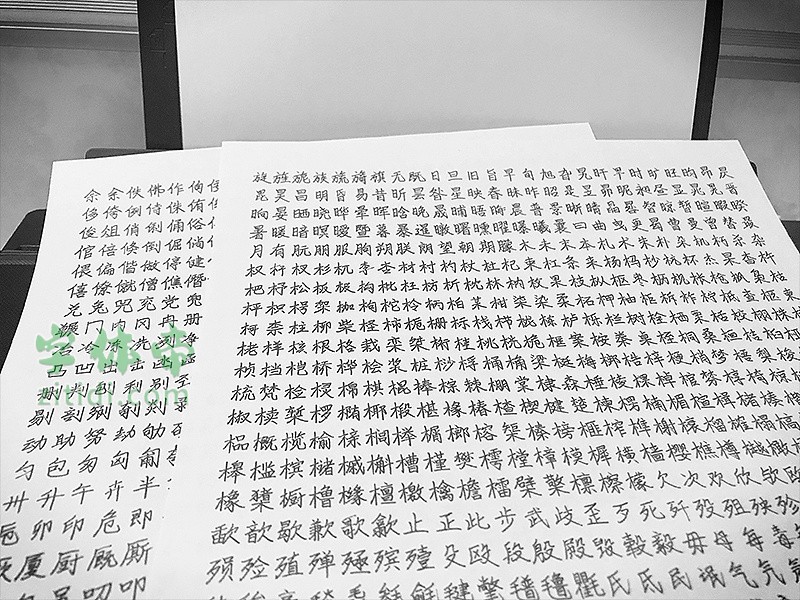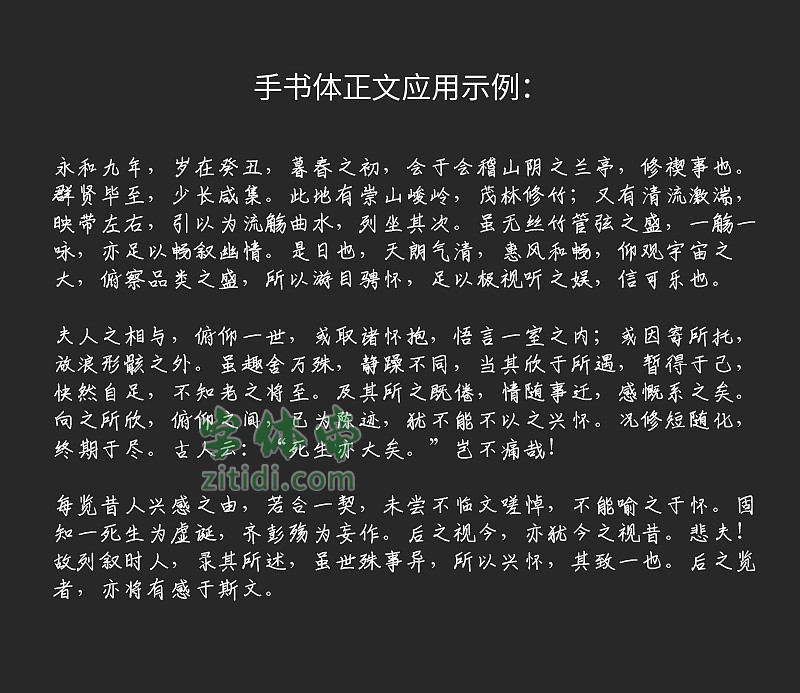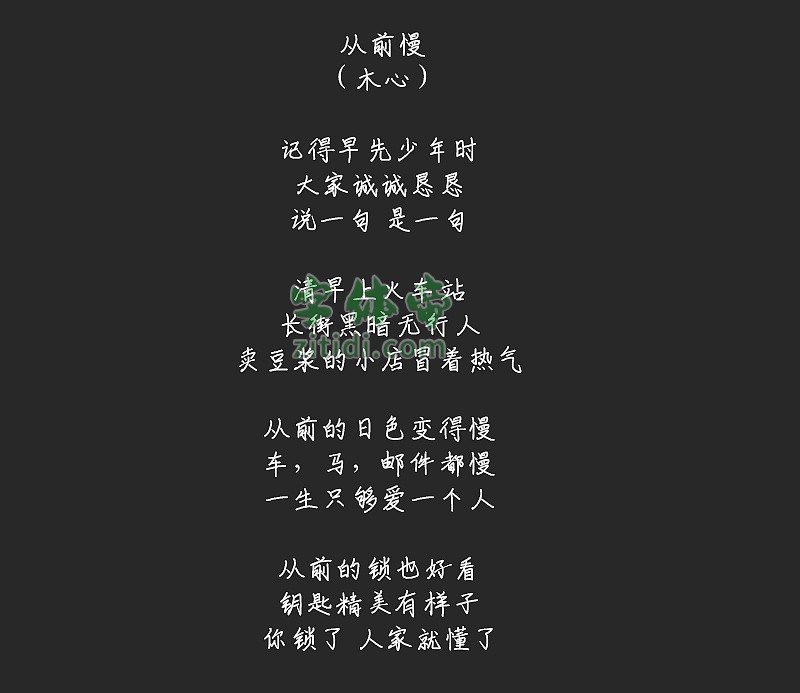
手书体字体信息
手书体
字体名称: 手书体
字体风格: 手写体
这款字体按照GB2312标准, 共做了基本汉字6763个 。这款字体风格为手写风格,可以用于slogan、banner、海报、商标等设计里面。这款手写字体字型十分漂亮,强烈推荐。
手书体”是一款书写很新颖的字体,字体大方,适合各种设计作品使用!欢迎下载!